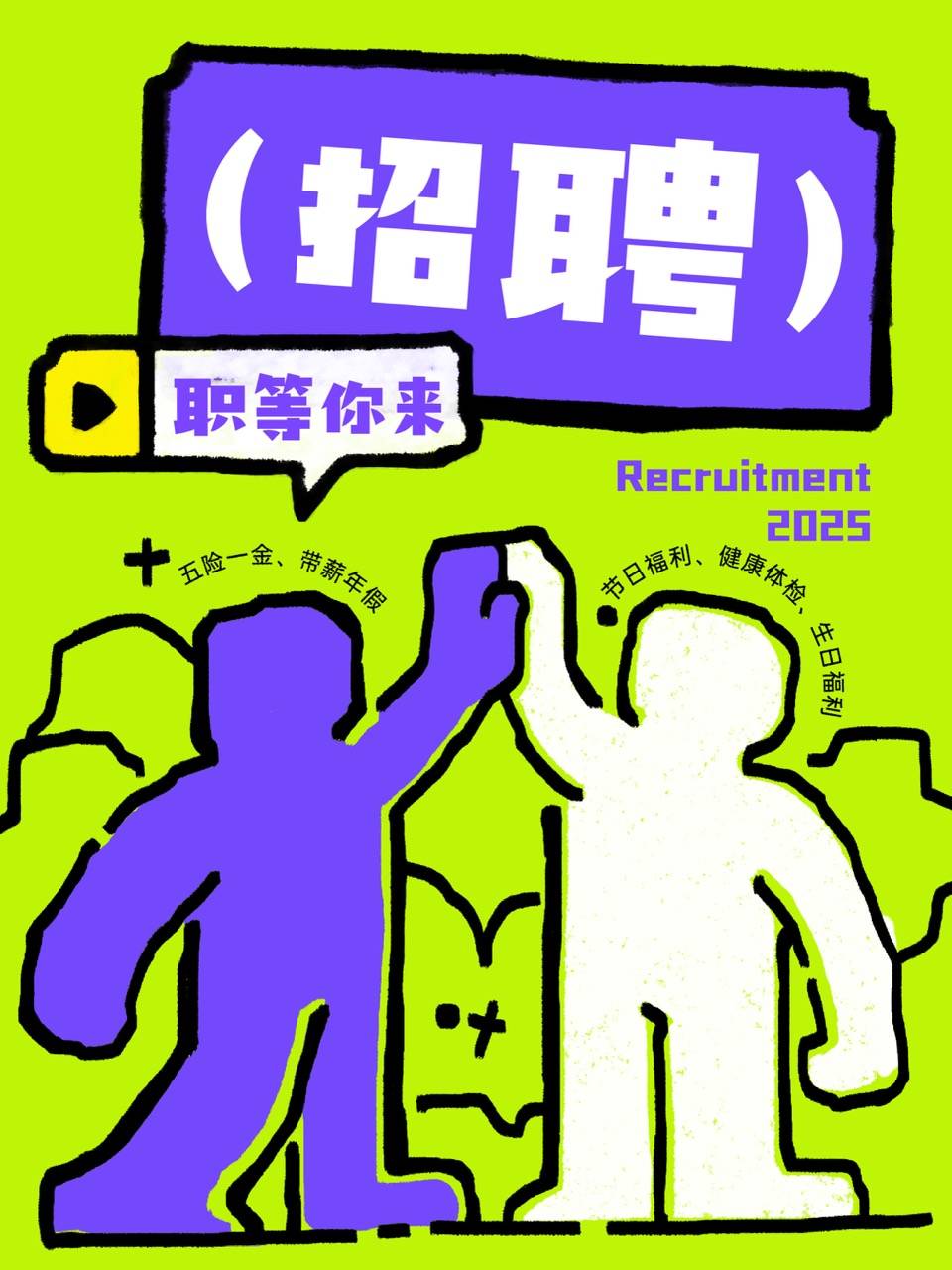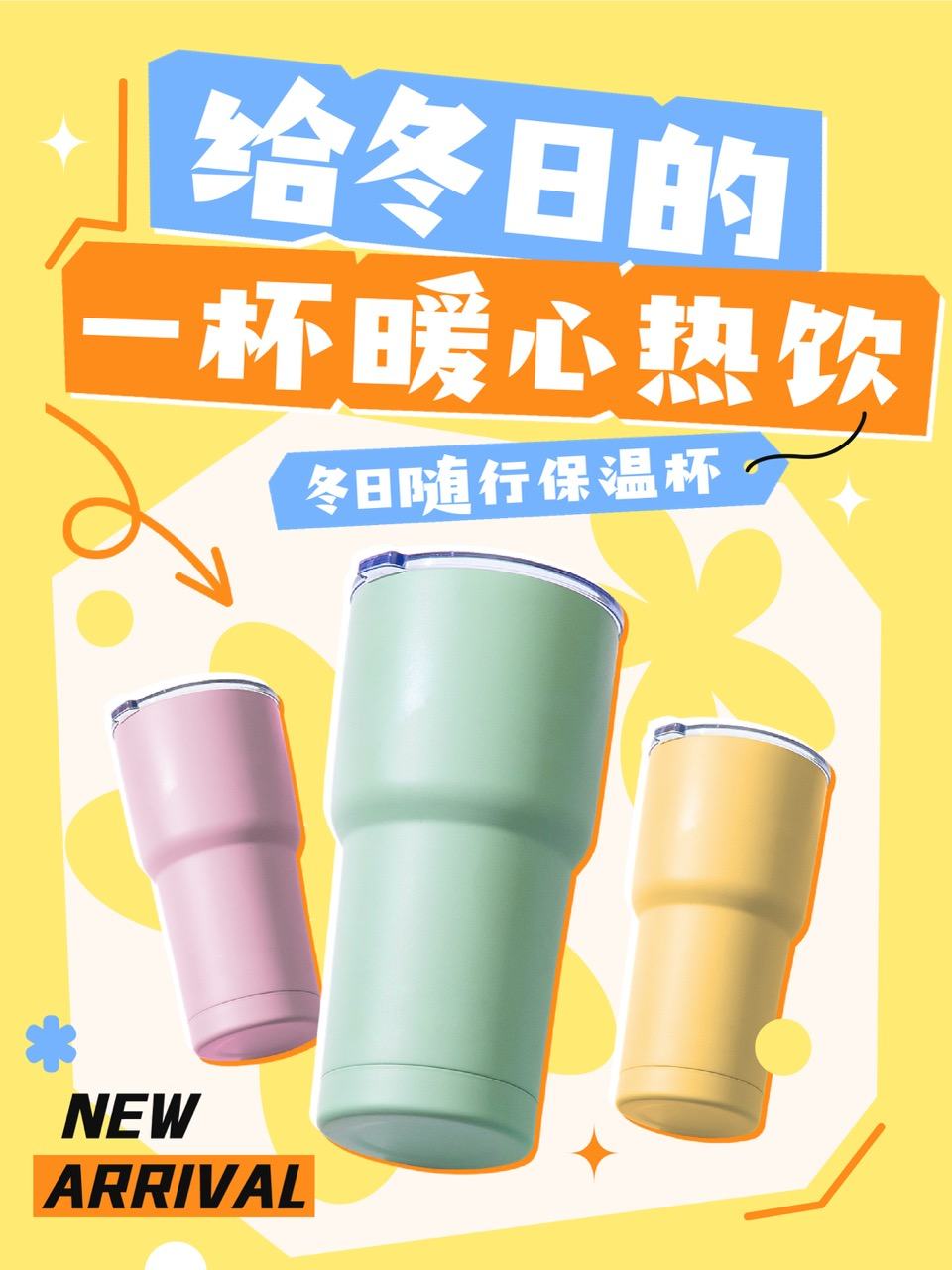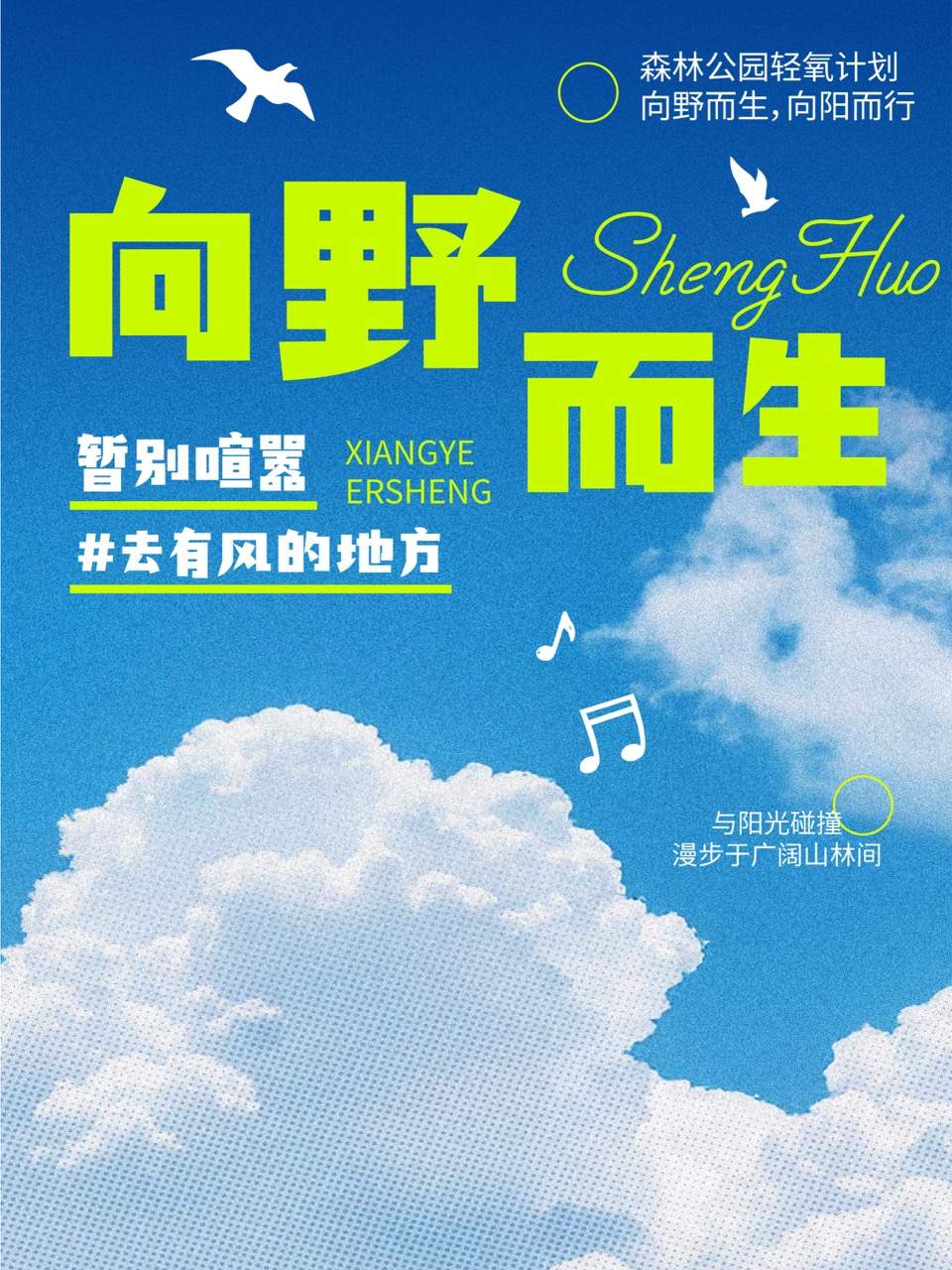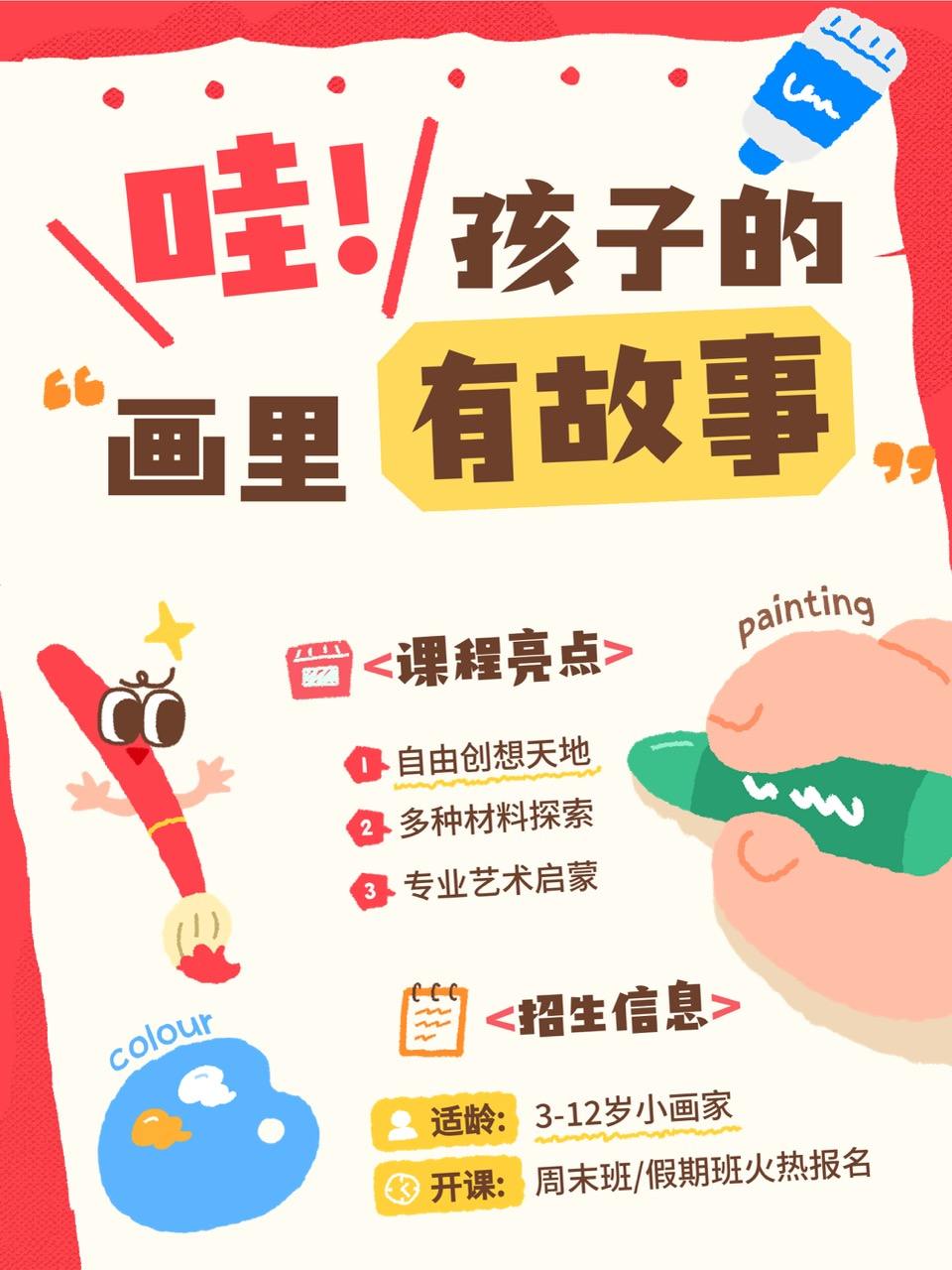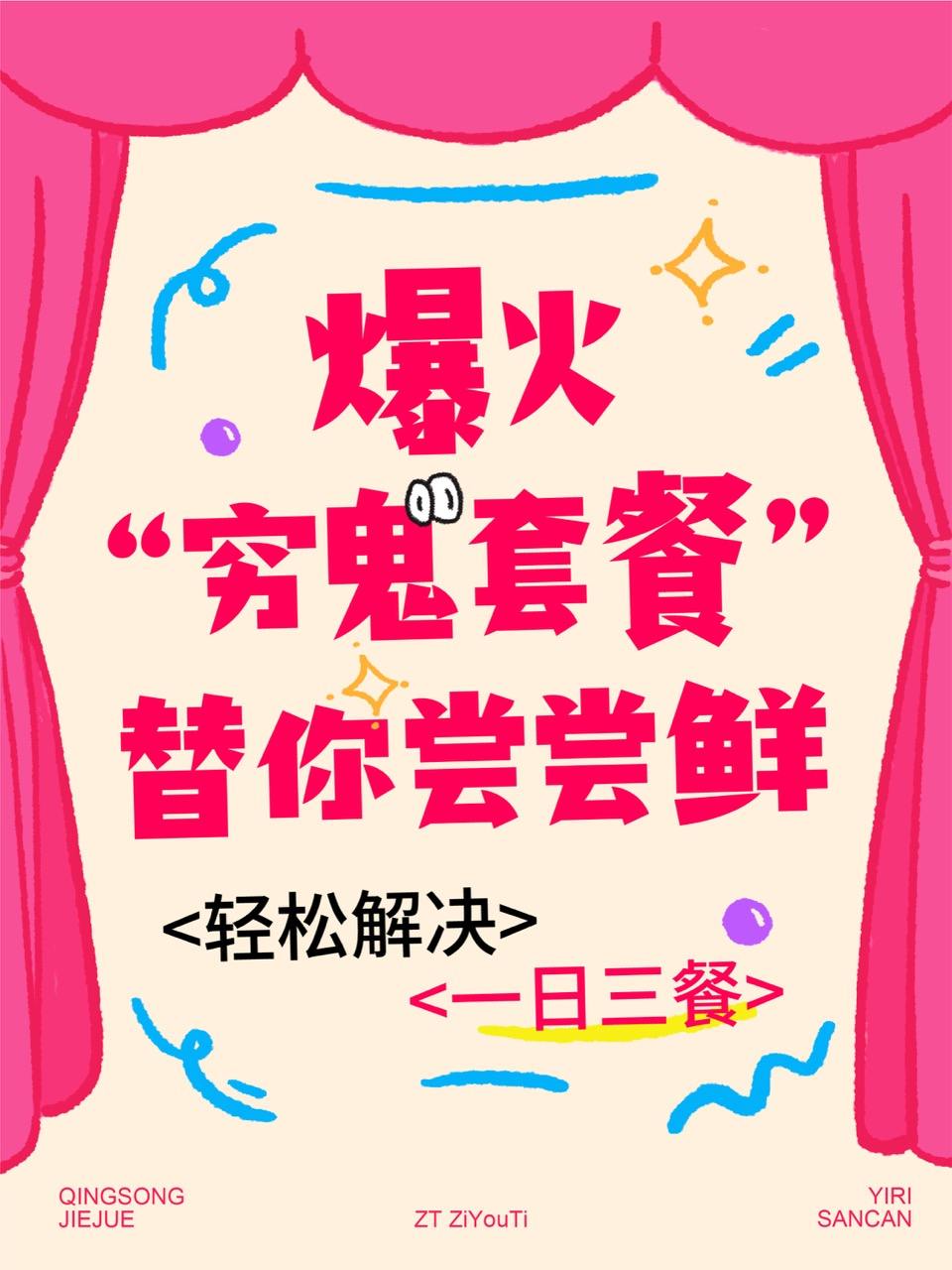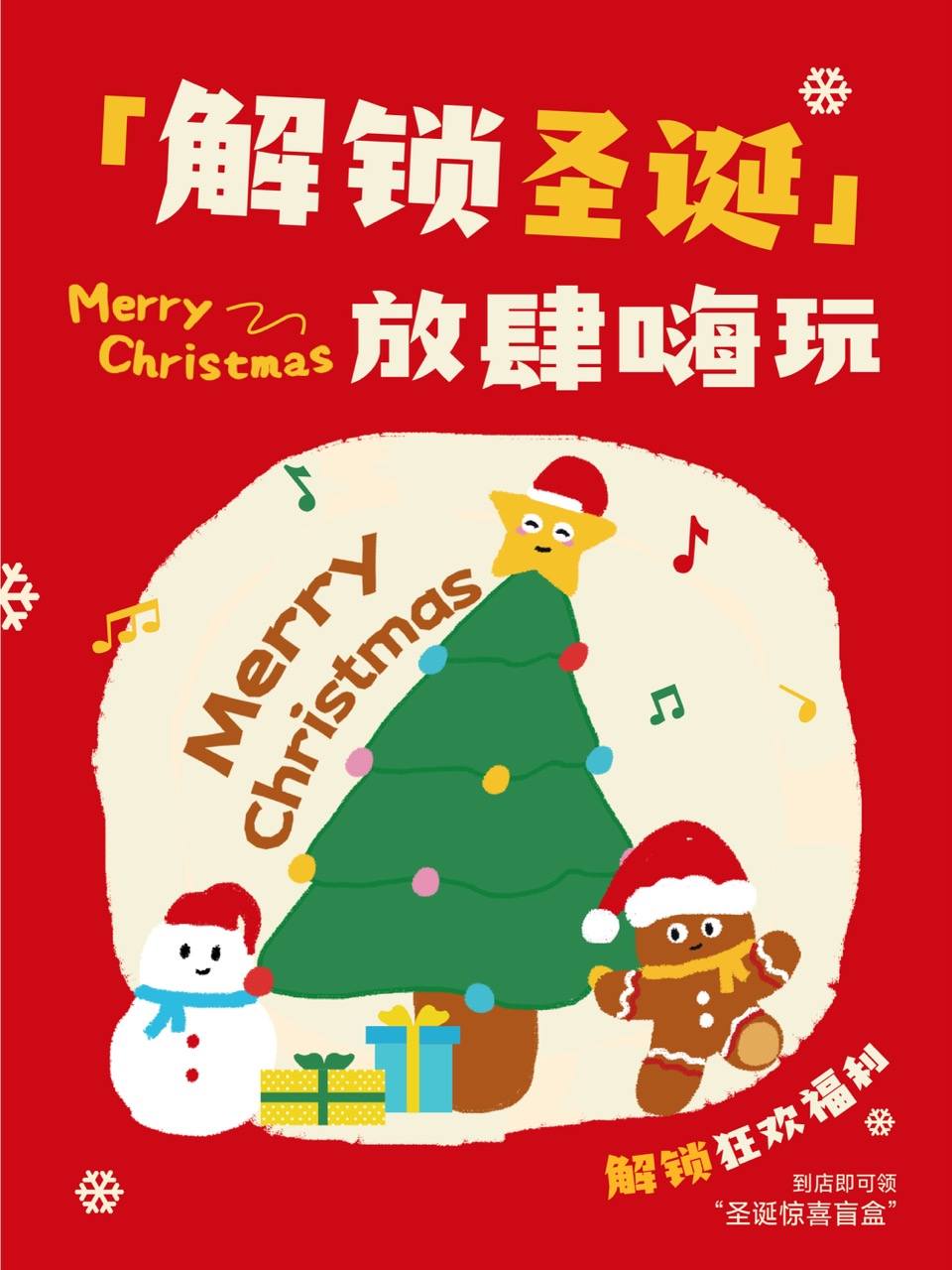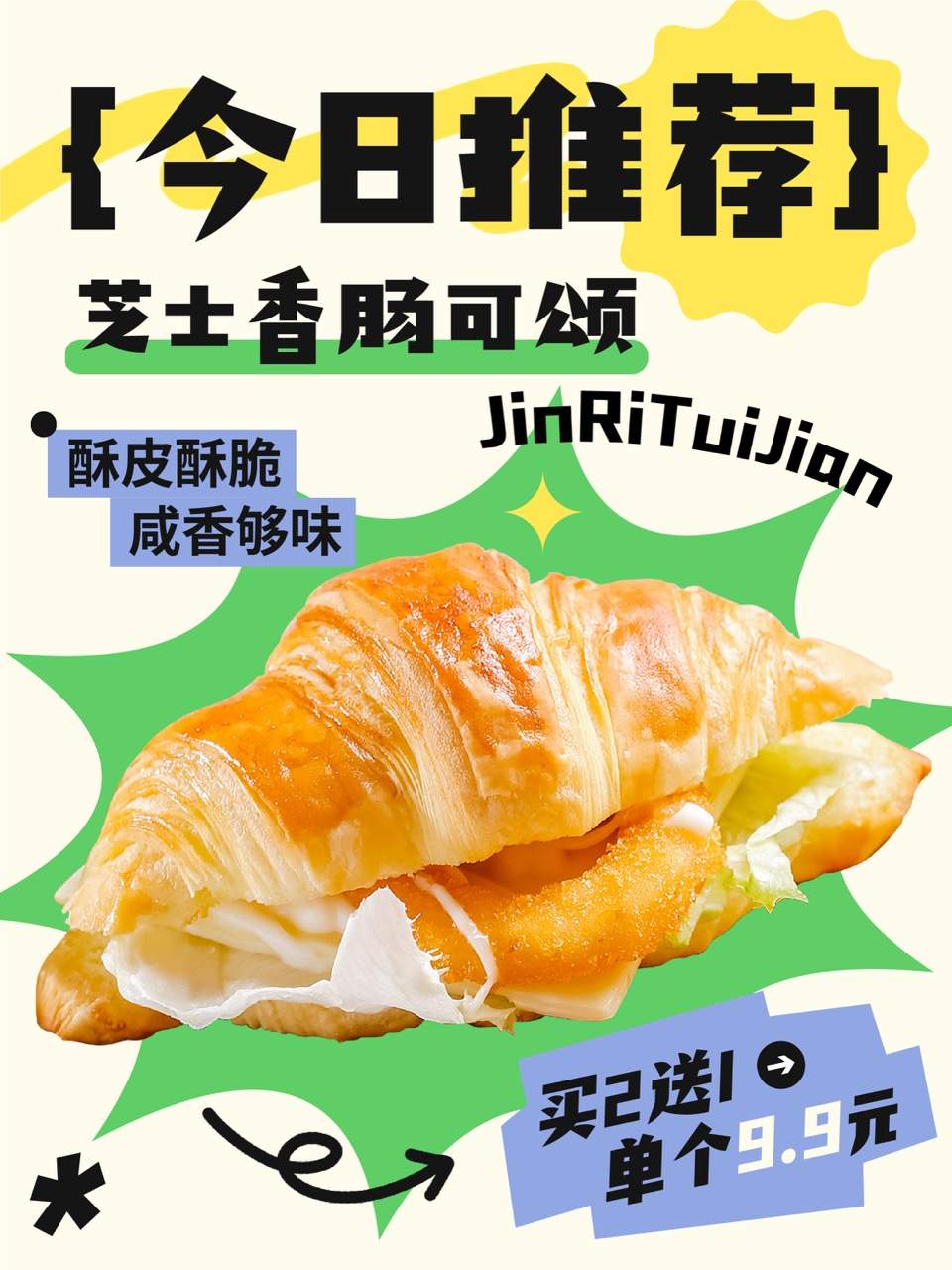
卓特自由体 灵动自由 张扬有力
字形结构宽阔,大小错落,节奏感强烈。笔画粗实有力,几何感强,整体风格张扬惊艳,极具视觉冲击力。
• 字形结构宽阔,大小错落
• 笔画粗实有力,几何感强
• 风格张扬惊艳
这是一张儿童绘画课程海报,主题是“哇!孩子的画里有故事”。课程亮点有自由创想天地、多种材料探索和专业艺术启蒙。招生对象是3到12岁的小画家,周末班和假期班正在火热报名。-刊刻Kntuk